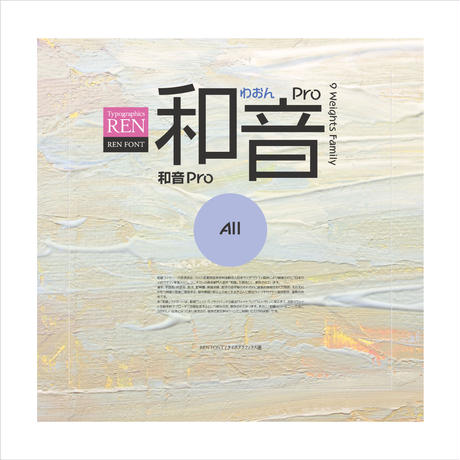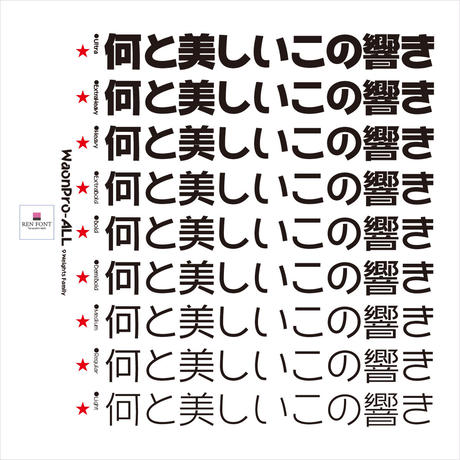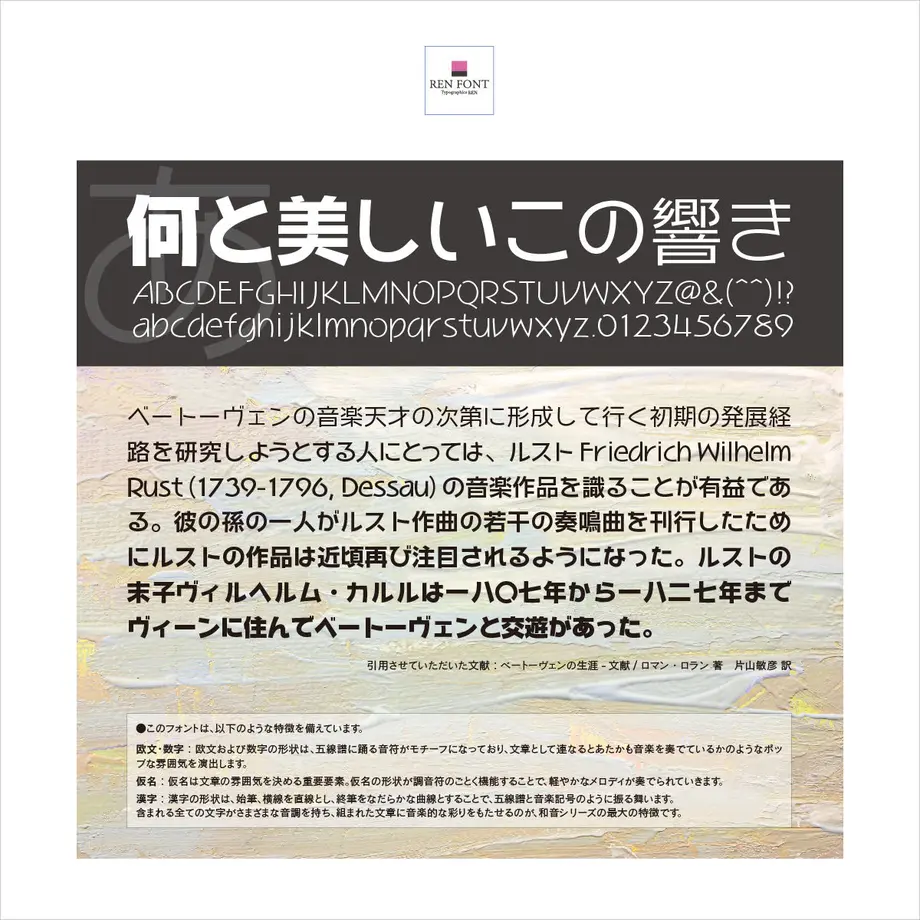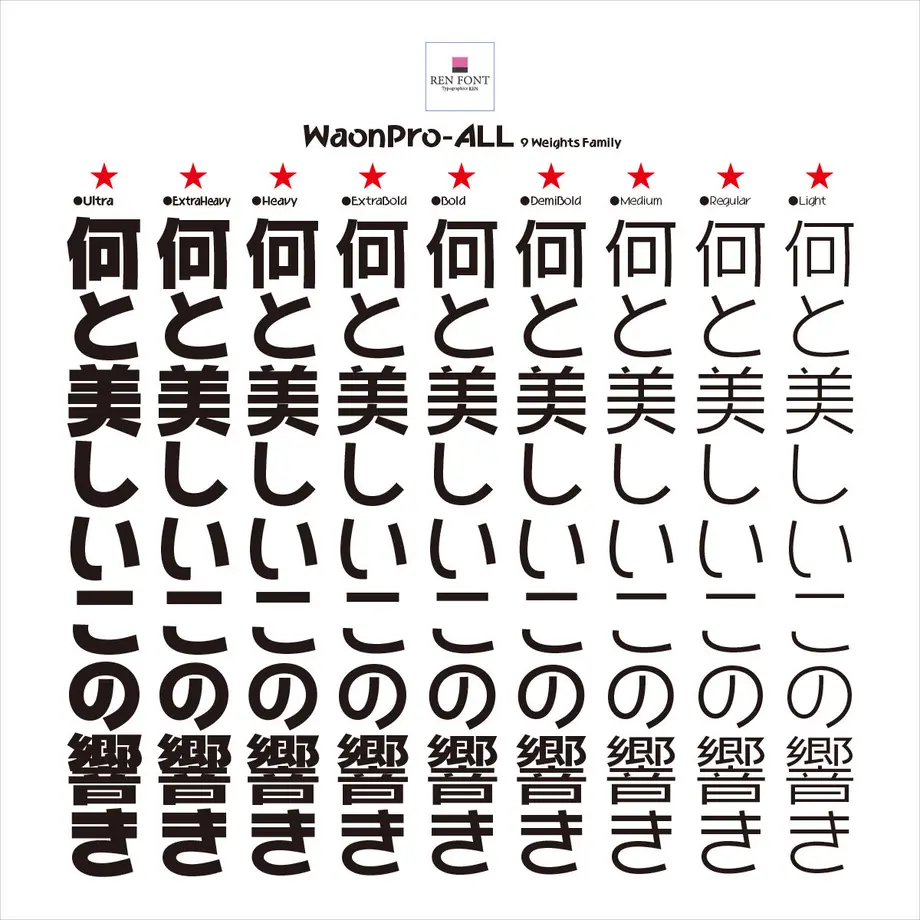
和音Pro-All Win
和音シリーズの各書体は、2005年度特定非営利活動法人日本タイポグラフィ協会により開催された「日本タイポグラフィ年鑑2005」コンテストの書体部門入選作「和音」を源流とし、制作されています。
漢字、平仮名、片仮名、欧文、記号類、用途字種、数字の各字種のそれぞれに音楽的特徴をもたせ設計、それぞれがもつ特徴が見事に調和する、制作期間2年以上の全てを注ぎ込んだ弊社タイプデザイナー金井和夫、渾身の労作です。
本「和音」シリーズは、最細ウェイト「L(ライト)」から最太ウェイト「U(ウルトラ)」に至るまで、合計9ウェイトを数学的アプローチで中間生成するという試みの元、制作されております。まさに「和音=ハーモニー」の名にふさわしい出来となっておりますので、是非さまざまなシーンでご利用いただければ幸いです。